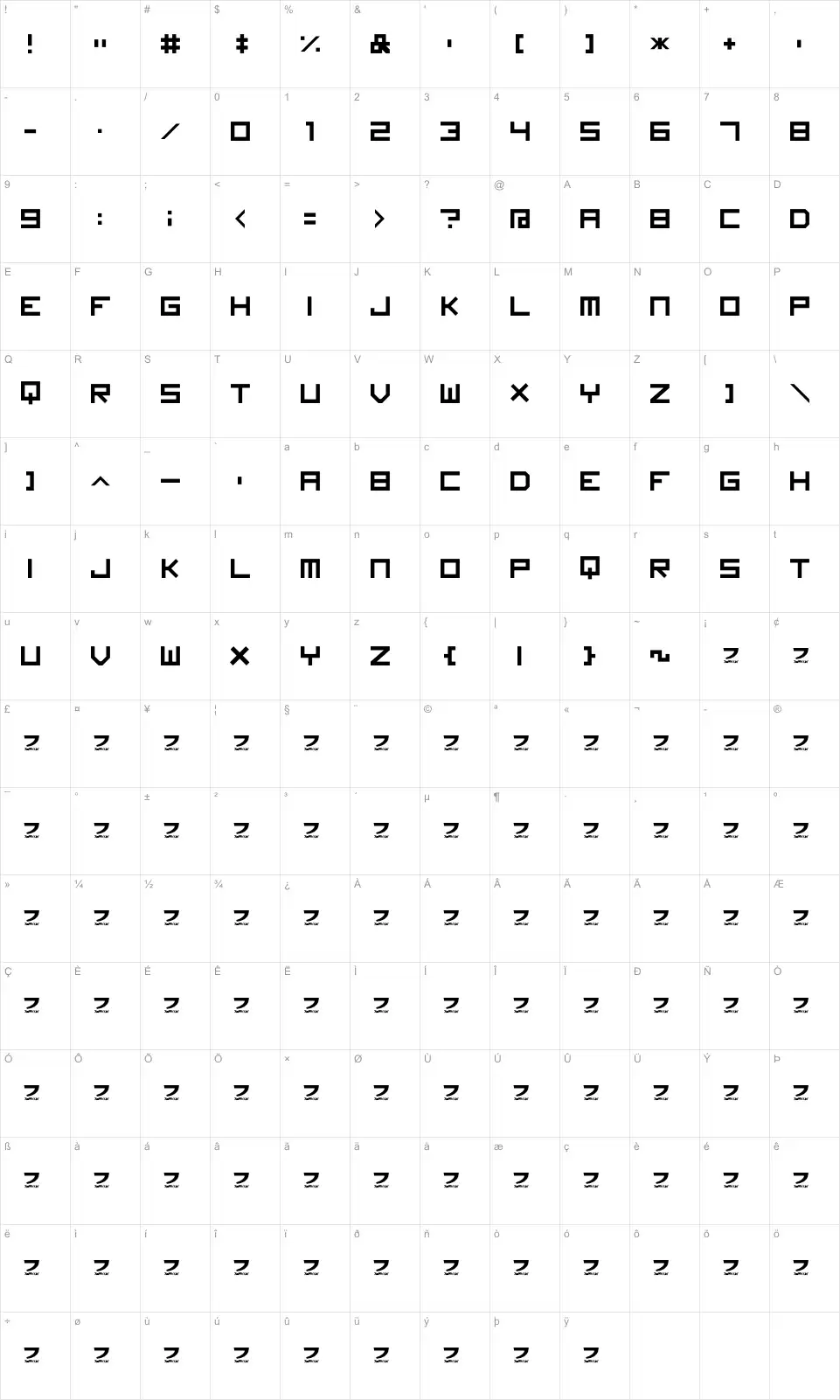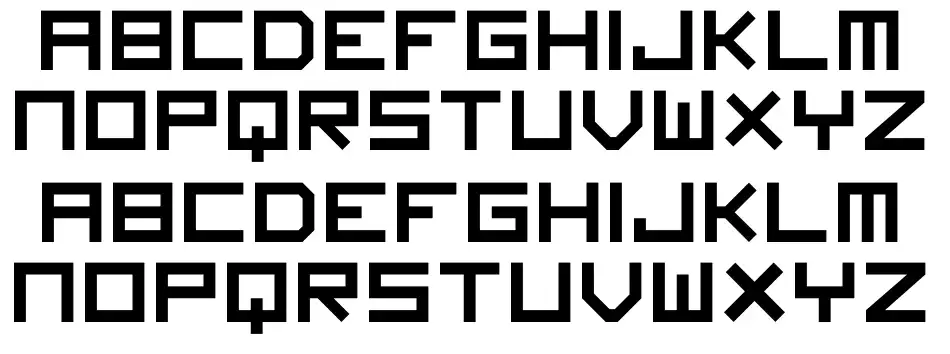
Imagine Font
Descubra a fonte Imagine Font criada pelo designer jooki. Esta tecnológica e moderna fonte do gênero Techno está disponível para download e visualização personalizada online. Tornar o seu texto único e único é uma aventura de apenas um clique. Licenciada para uso pessoal, a fonte Imagine Font está disponível em formatos OTF e TTF. Com seu design Square, ela se destaca na categoria tecnológica. Adicionada ao banco de dados em 12 de julho de 2022, a fonte já teve mais de 10.000 downloads. Com um tamanho de apenas 6 KB, Imagine Font é uma escolha inteligente para aqueles que buscam um estilo clean e eficaz. Visite o site do designer jooki em https://www.jooki.de para mais informações sobre outras fontes e projetos.
Categoria: Techno › Square
Designer: jooki